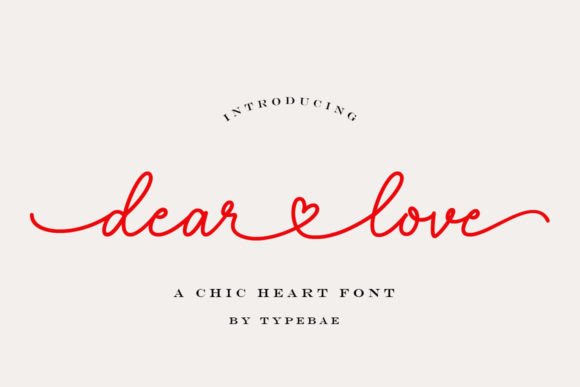
Dear Love
Nếu bạn đang tìm kiếm các tài nguyên chất lượng cao như Dear Love, gói cao cấp này là một lựa chọn tuyệt vời cho các dự án sáng tạo của bạn.
Cho dù bạn đang tạo sản phẩm POD (In theo yêu cầu), thiệp mời đám cưới hay đồ họa mạng xã hội, Dear Love đều là một sự lựa chọn lý tưởng.